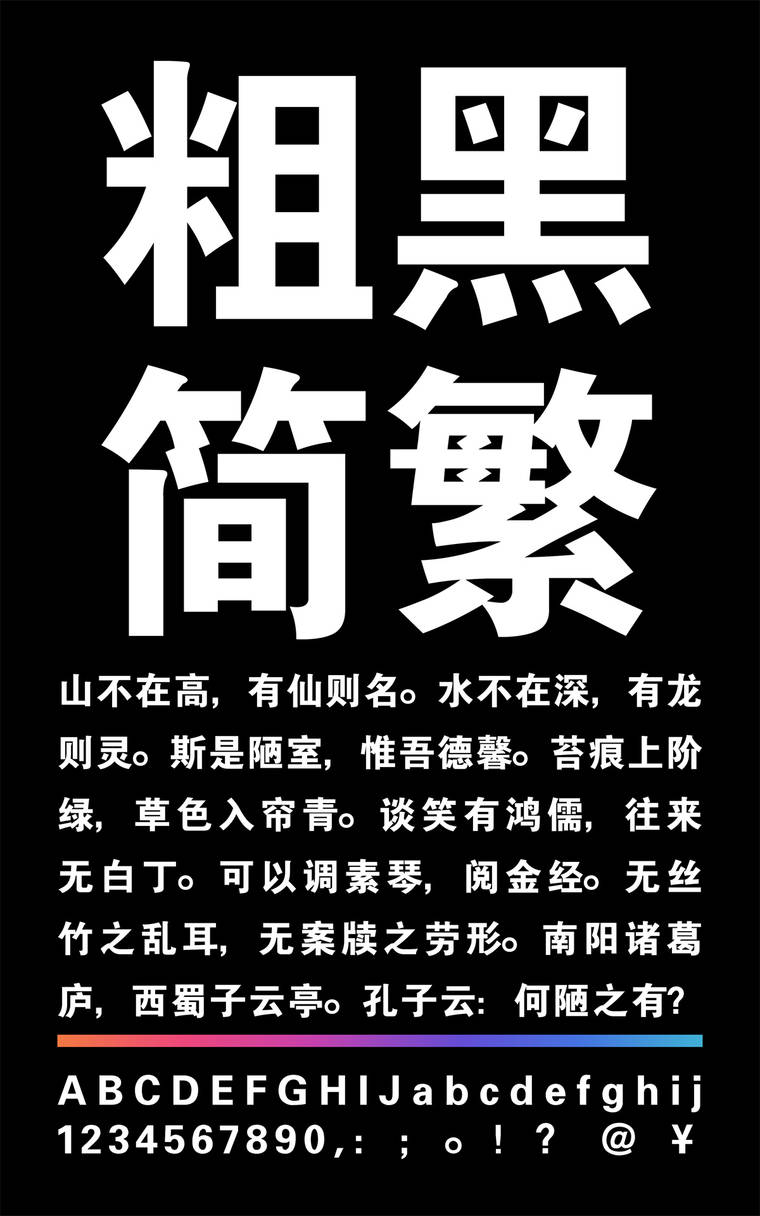
锐字云字库粗黑简繁
锐字云字库粗黑简繁字体介绍
字体特征:笔画粗壮有力,字形结构严谨,朴素大方,稳重醒目,特点是没有衬线装饰,字面呈正方形的粗壮字体,笔划粗壮有力,撇捺等笔画不尖,字形端庄,笔画横平竖直,全部一样粗细,结构醒目严密。方正、粗犷、朴素、简洁、无装饰、横竖笔形粗细视觉相等、笔形方头方尾、黑白均匀,因此非常醒目,运用广泛。适用于标题,导语,标志,标题或需要引起注意的醒目按语或批注等。